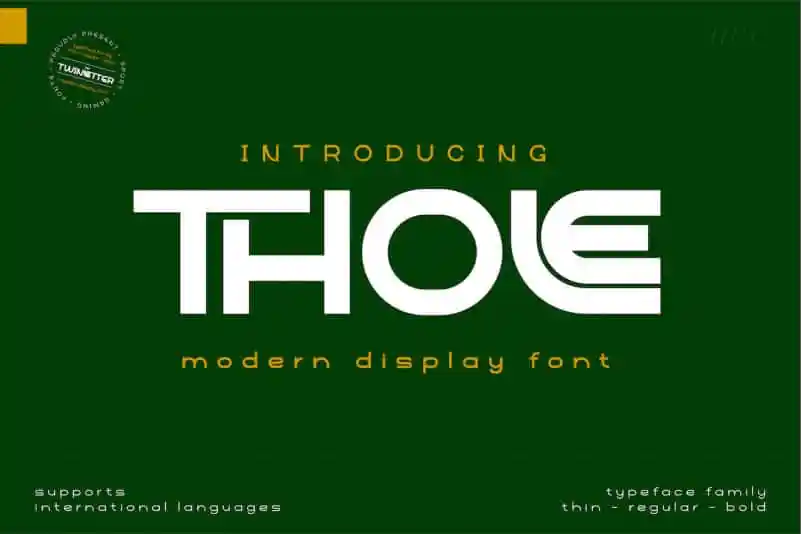
Thole Display Font – Download Grátis
Introduzimos a Thole Display Font, uma família elegante e limpa de san serif que destaca seu estilo feminino ou masculino. Esta fonte não apenas se encaixa perfeitamente para projetos com temas delicados ou robustos, mas também oferece um forte impacto visual. Os espaçamentos entre as letras têm um formato característico, enquanto os ângulos desta fonte contêm ligaturas e alternativas para atender às suas necessidades. A Thole Display Font é perfeita para quem deseja destacar-se em seus projetos de design.